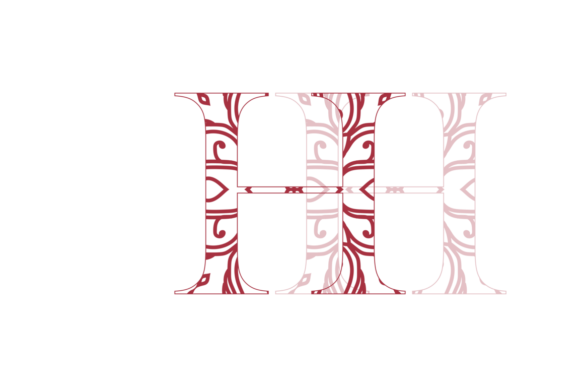
Mandala Font Abc Floral Pattern Design
適切なデザイン要素を見つけるのは難しい場合がありますが、Mandala Font Abc Floral Pattern Designは作品を即座に引き立てる優れたコレクションを提供します。
POD(オンデマンド印刷)製品、結婚式の招待状、またはソーシャルメディアのグラフィックを作成している場合でも、Mandala Font Abc Floral Pattern Designは理想的です。